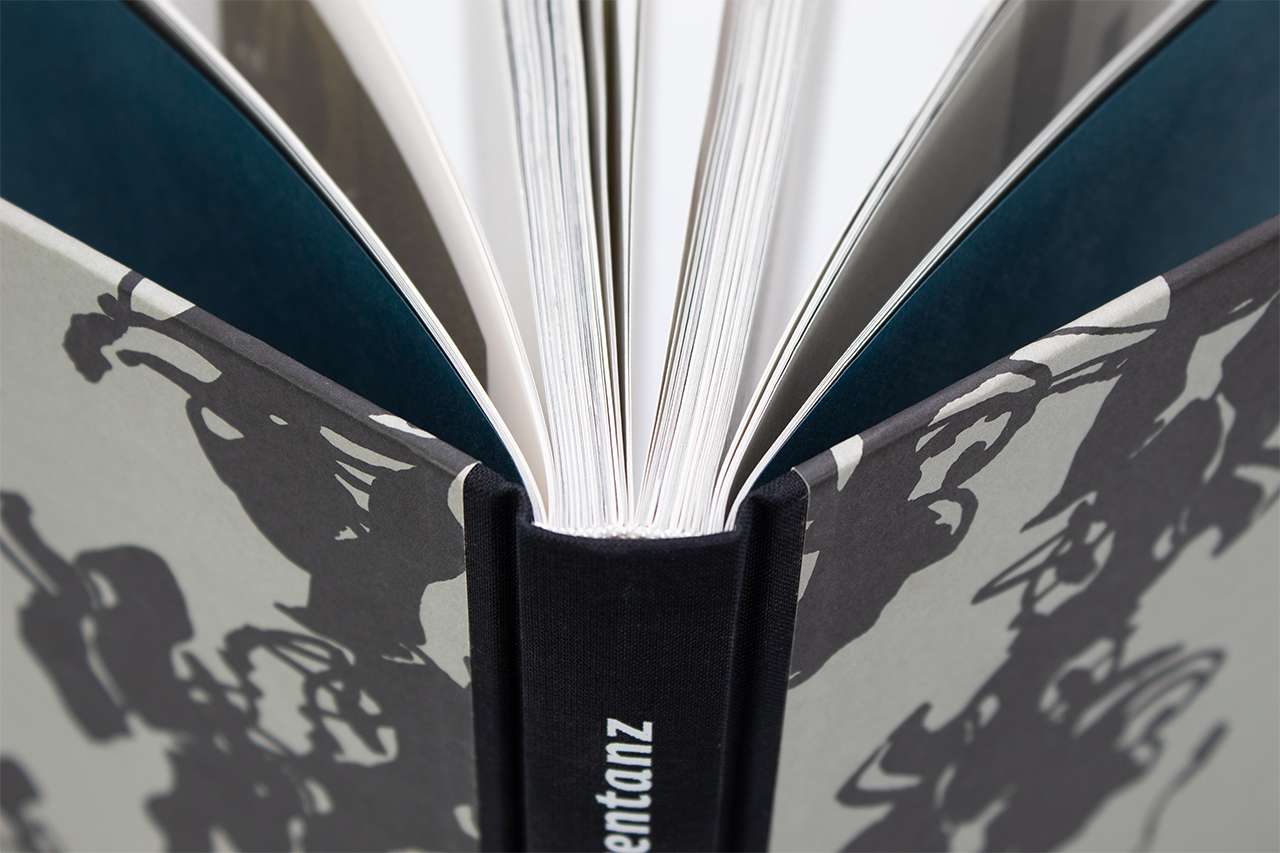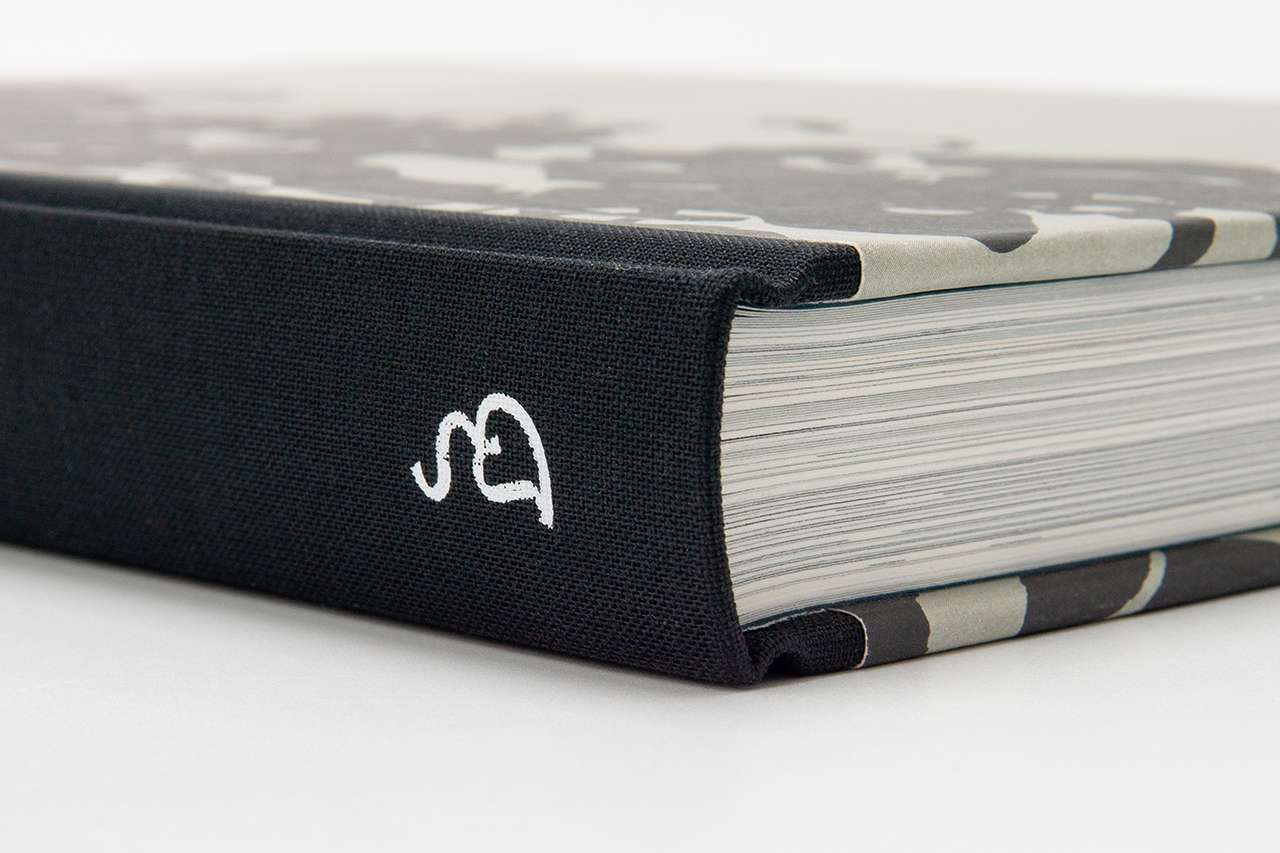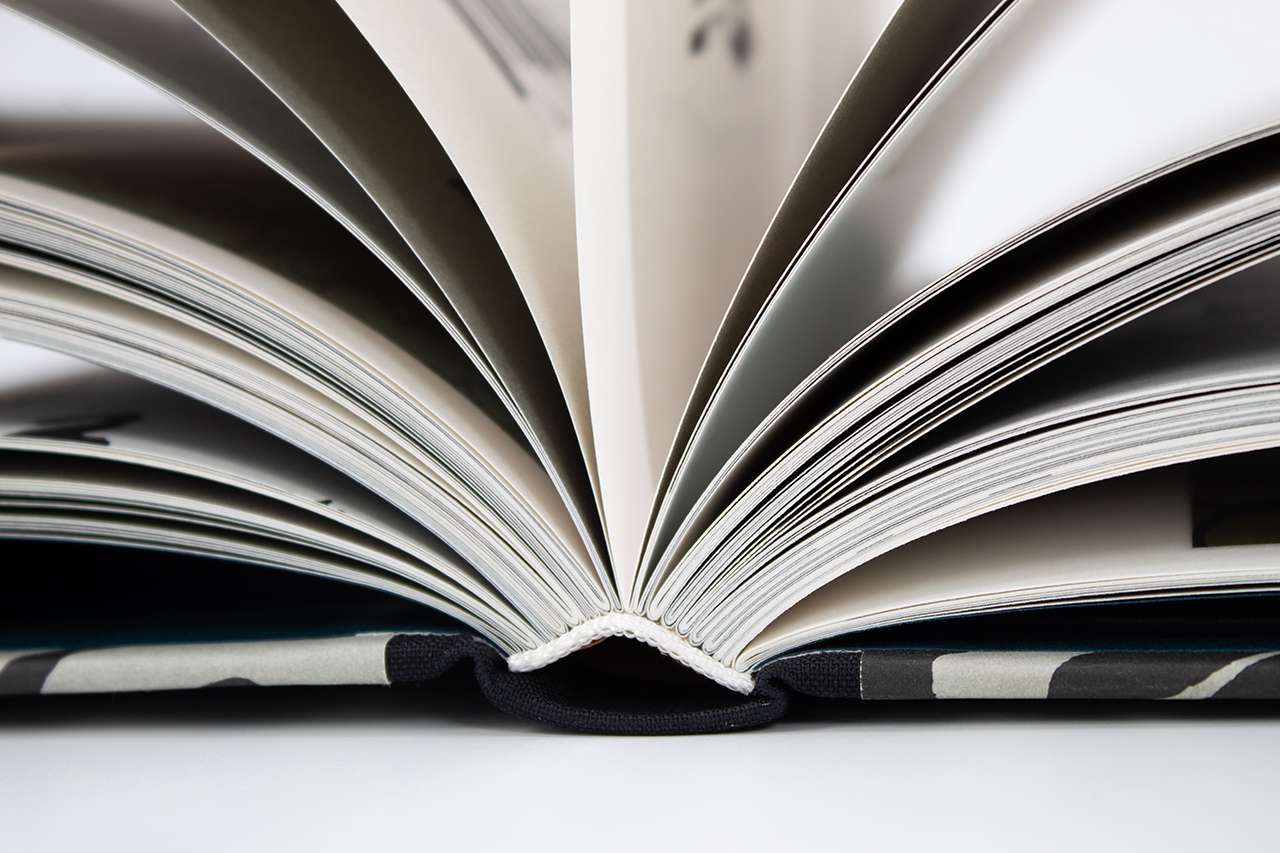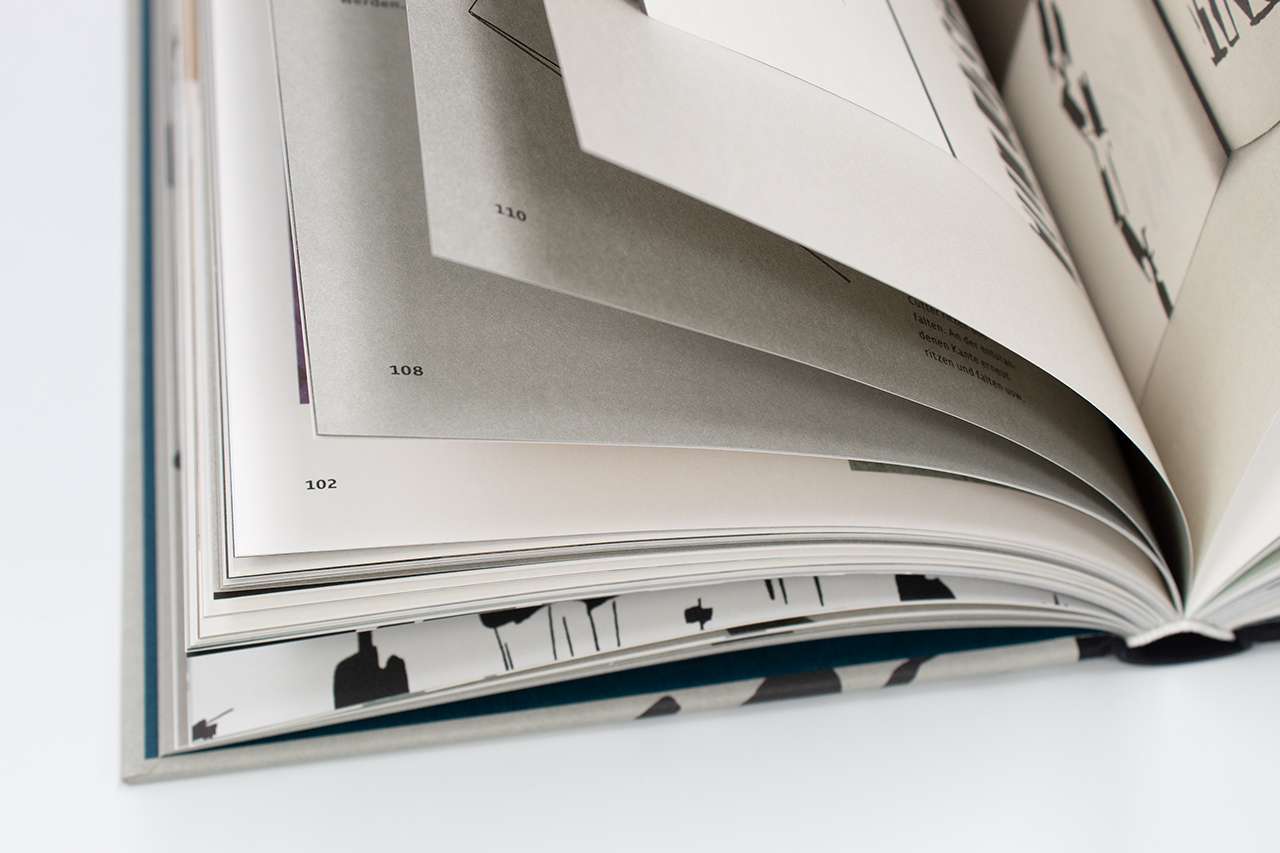
Eine Art antiautoritäre Schrifterziehung. Ein praxiserprobtes Kalligrafiekonzept.
Schräge Töne sind willkommen. Freejazz für die Hand. Ansteckende Lebensfreude auf Papier. Mit diesem Kalligrafiekonzept hat Hans-Jürgen Willuhn Generationen von Gestalter:innen dazu gebracht, das Charakteristische ihrer Handschrift zu erkunden, herauszuarbeiten – und zu perfektionieren.
Willuhn überlässt die Suche nach dem eigenen Duktus und der persönlichen Schreibspur nicht allein der Hand, sein leicht anarchischer Ansatz fordert vollen Körpereinsatz, es gibt kein »richtig« und »falsch«, stattdessen gibt’s viel zu entdecken!
Pauline Altmann hat diese besondere Schrifterziehung genossen und sich mit diesem Buch zum ersten Mal als herausragende Buchgestalterin bewiesen. (Nicht die erste übrigens, die mit einem Buch bei Schmidt den Weg in den Olymp der Buchgestaltung antrat.)
Tintentanz
Die Ausdruckskraft der eigenen Handschrift entdecken.
Ein Kalligrafiekonzept
Gestaltung: Pauline Altmann